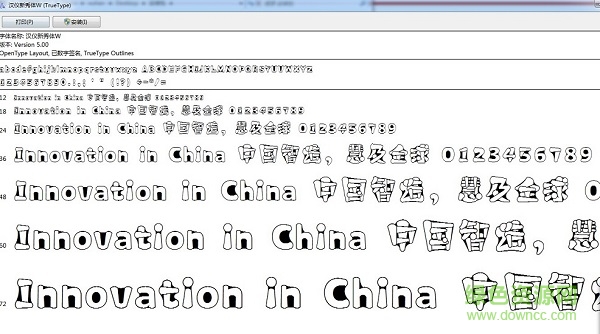
漢儀新秀體字體
漢儀新秀體是一款豐滿漂亮的空心藝術(shù)字體,結(jié)構(gòu)規(guī)范,筆畫前后統(tǒng)一,適合用于計(jì)算機(jī)制作、墻報(bào)廣告、書刊封面等各個(gè)領(lǐng)域,綠色資源網(wǎng)為大家免費(fèi)提供漢儀新秀體w和漢儀新秀體簡的打包合集,歡迎免費(fèi)下載!
漢儀新秀體特點(diǎn)
結(jié)構(gòu)獨(dú)出心裁,布局耐人尋味,具有美觀大方,便于閱讀和識(shí)別等優(yōu)點(diǎn)。
漢儀新秀體